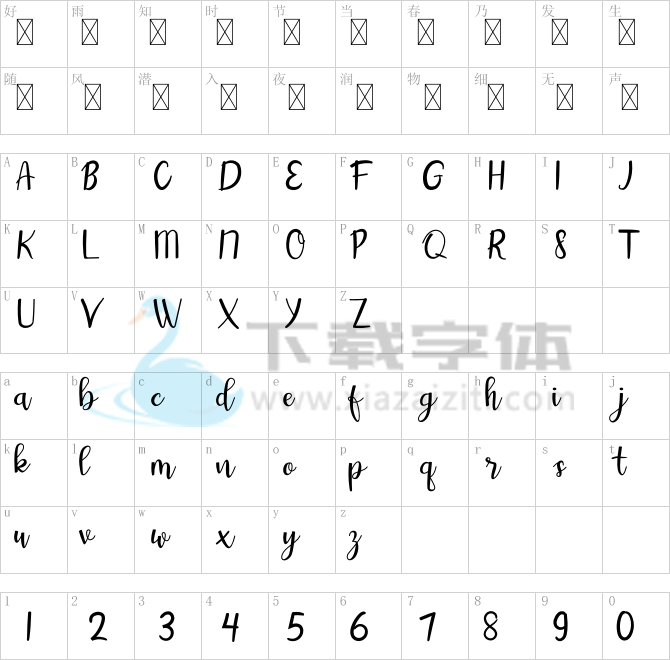
Aintya Beauty.otf字体下载
Aintya Beauty.otf字体下载,这款字体结构工整、笔画清晰,兼顾美观与易读性,适用于标题、正文、海报、包装、LOGO 等多种场景。字形优雅稳定,风格百搭耐看,适配日常排版与创意设计,让文字呈现更舒适、更具质感。Aintya Beauty.otf字体下载一笔一画,皆是细节,以均衡的比例、流畅的线条打造舒适视觉体验,字形端正大气,风格简约现代。无论是商业设计、品牌宣传还是日常排版,都能轻松驾驭,让文字更有格调与力量。Aintya Beauty.otf字体下载字体下载。